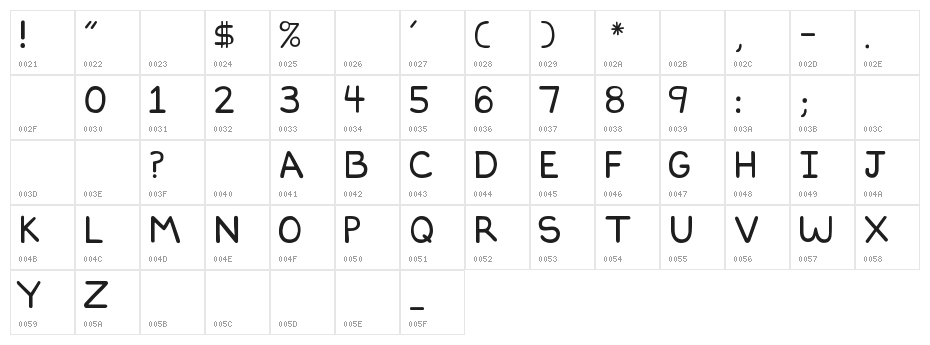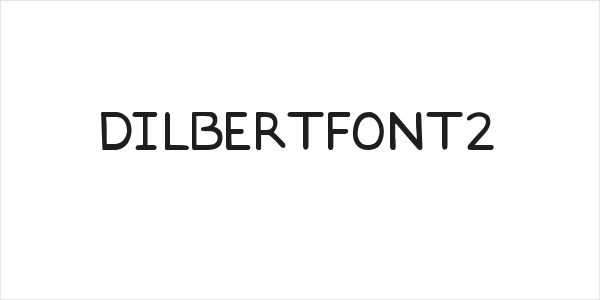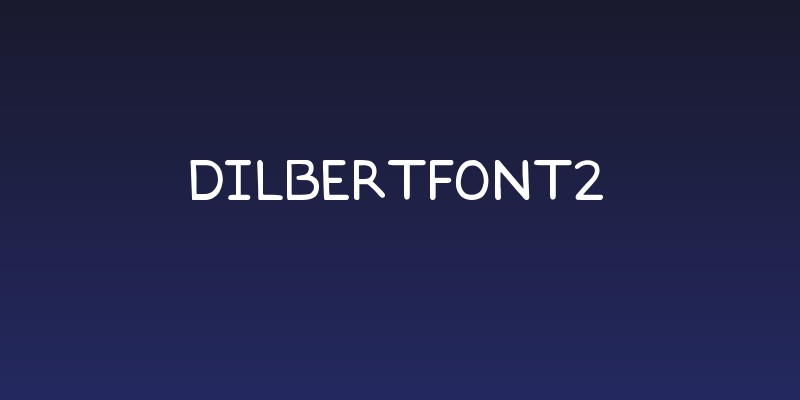
DILBERTFONT2 Font
| Gesamtstil | Playful |
| Vorgeschlagene Projekte | Ideal for children's books, casual branding, playful posters, and creative digital content. |